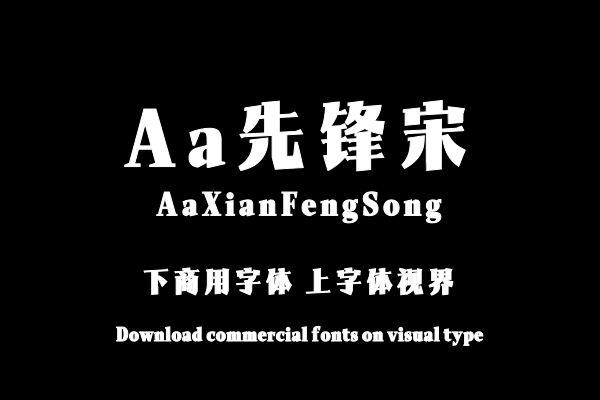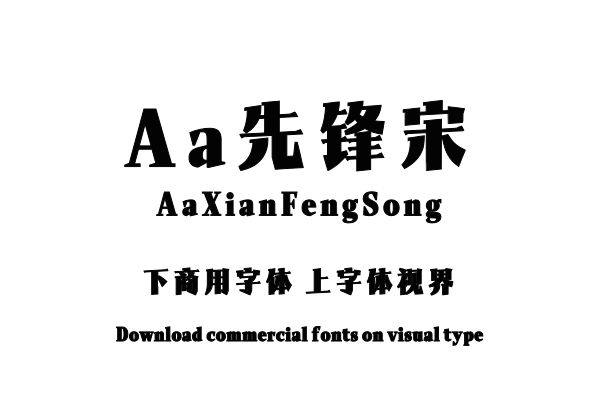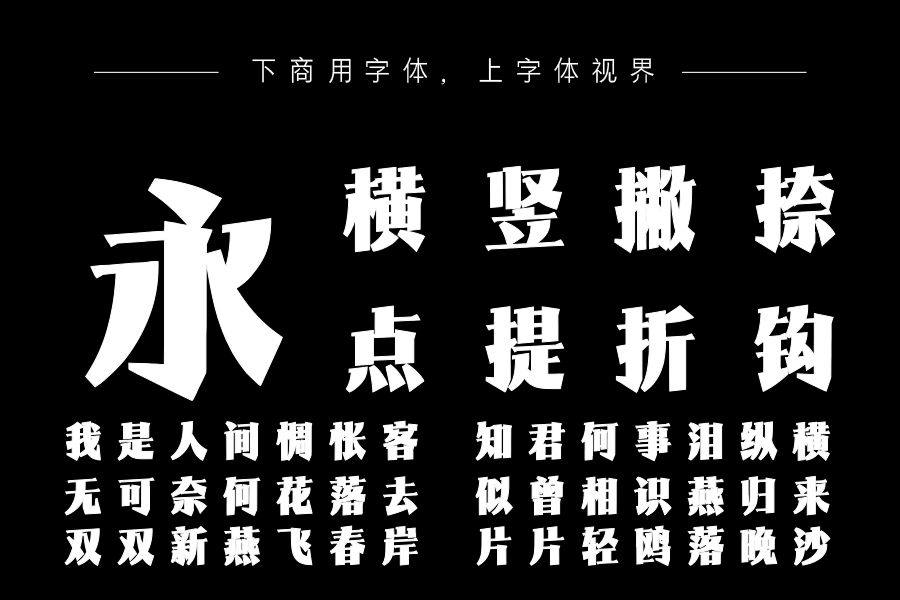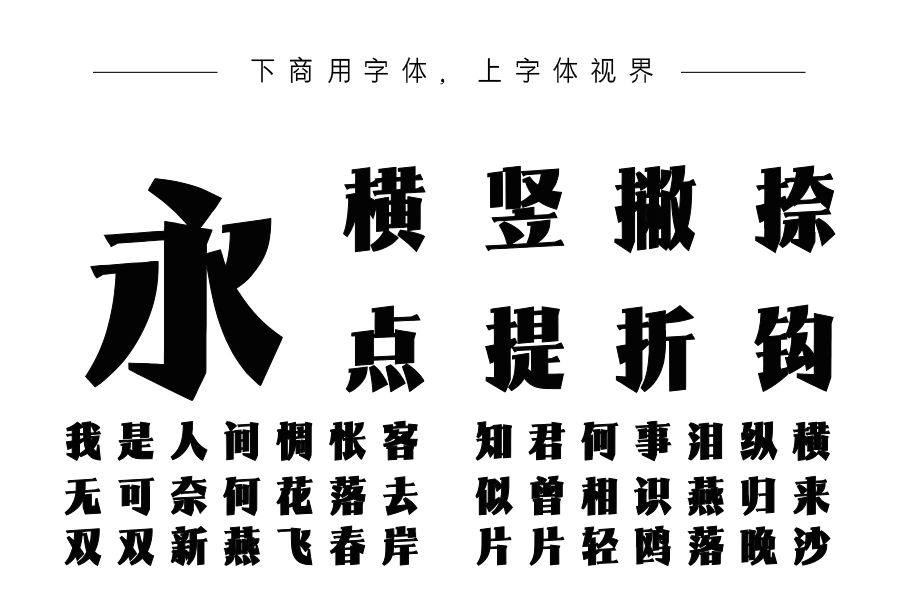
以宋体为基底,横向笔画微倾打破平正规整,实现传统底蕴与现代动感的平衡,区别于传统宋体的复古调性。高挑字形搭配简洁硬朗笔画,强化纵向挺拔感,形成独特锐利视觉标识,......购买须知:“下载服务费”与“字体VIP”所获得字体 仅用于个人非商用, 商用请联系付费授权。本字体为电脑用字,手机没有root权限不支持直接手机换字(手机如何root,请自行百度搜索教程)。购买前请先 了解清楚后再付款 ,字体为虚拟产品无法回收 一旦购买不支持退款。